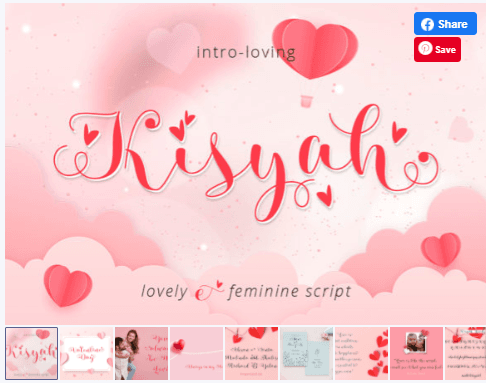
Kisyah Font
Kisyah - это романтичный и сладкий каллиграфический шрифт с персонажами, танцующими вдоль базовой линии. У него повседневный, но элегантный вид. Этот шрифт закодирован в кодировке PUA, что означает, что вы можете легко получить доступ ко всем глифам и штрихам!